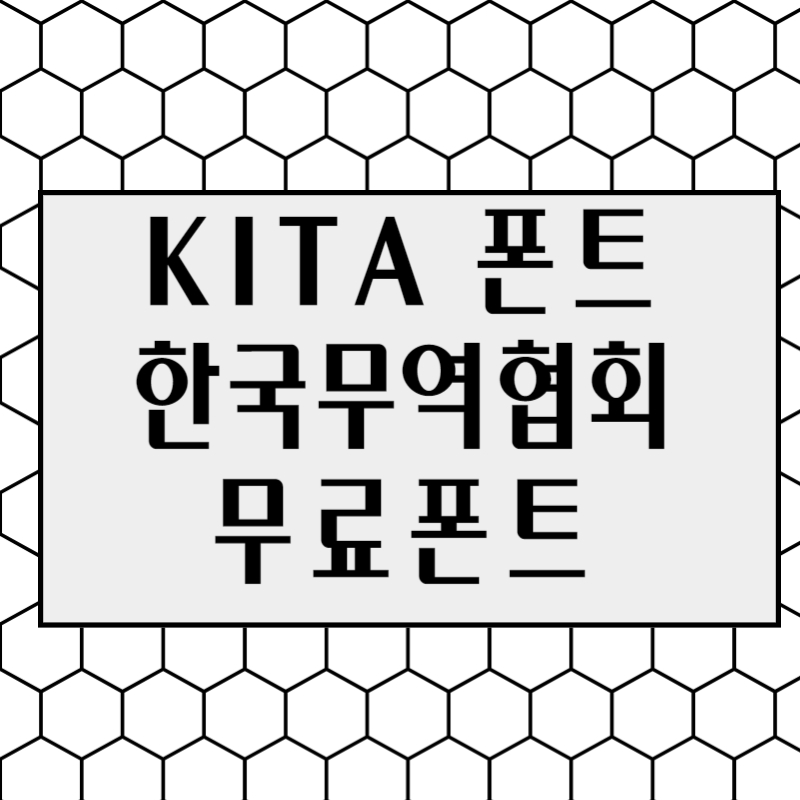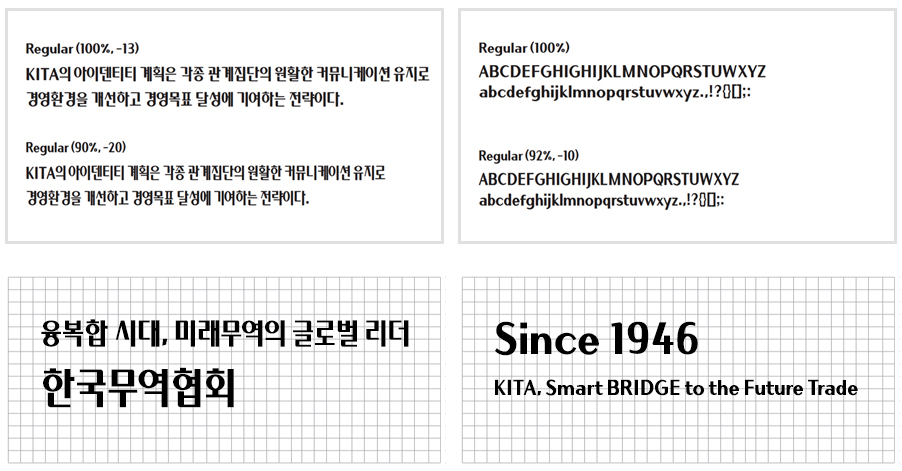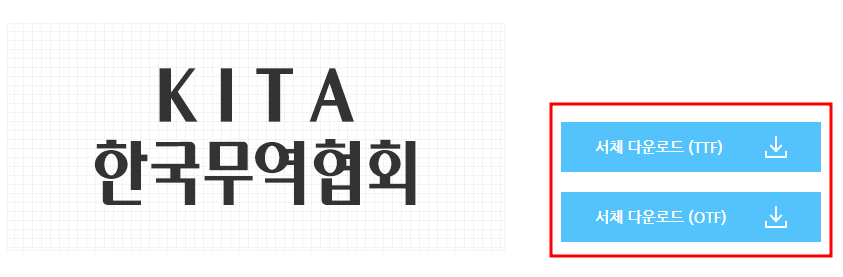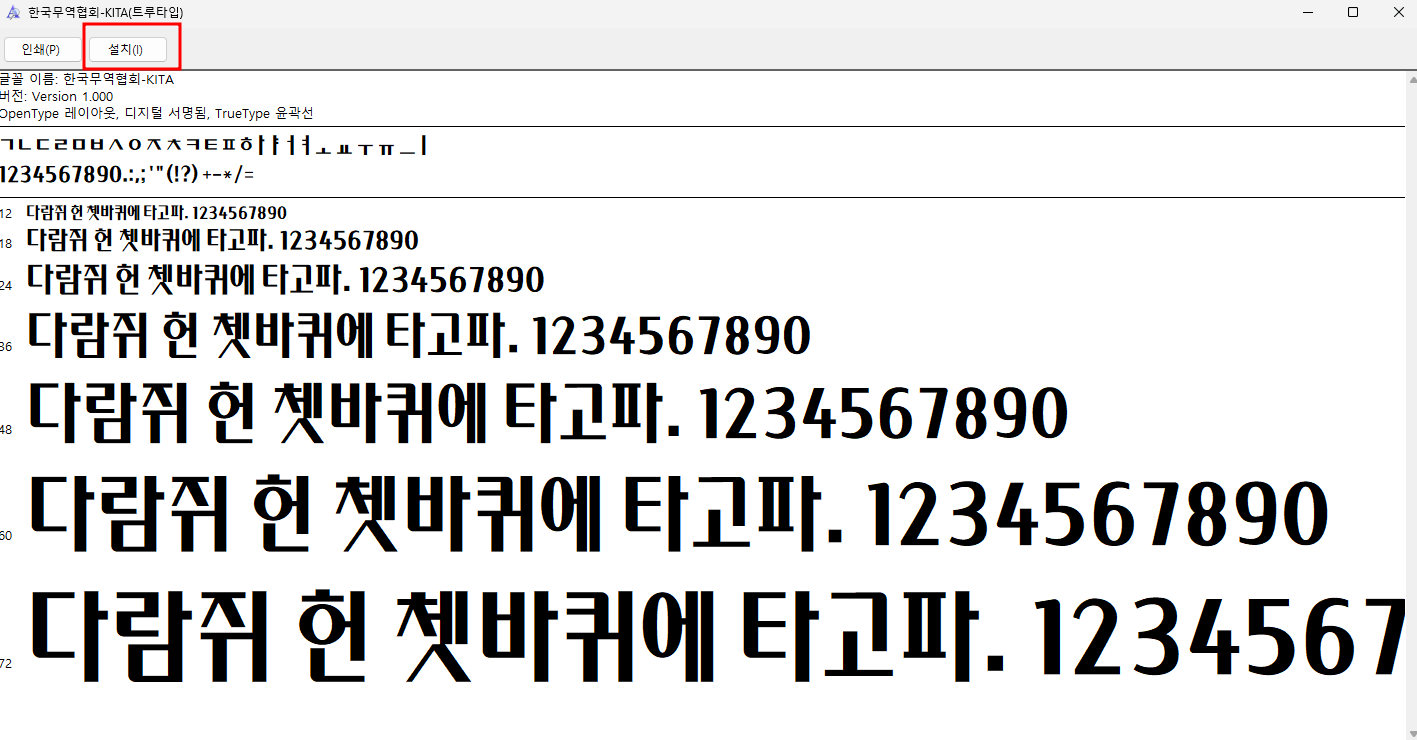
KITA 폰트입니다. 한국무역협회 전용서체로 무료로 다운 받을 수 있으며 자유롭게 사용가능합니다. 저작권 및 지적 재산권은 한국무역협회에 있습니다. 깔끔한 폰트로 사용하면 결과물도 예쁘게 나와서 저도 자주 사용하고 있습니다.
한국무역협회 전용서체는 우리나라 무역의 도약과 무역인들의 진취적인 모습을 상징하는 것으로 표현했습니다. 저작권에서 자유로운 폰트를 무역업계와 국민 편익 증진을 위해 한국무역협회에서 무료로 배포하고 있습니다.
KITA 폰트 활용예시